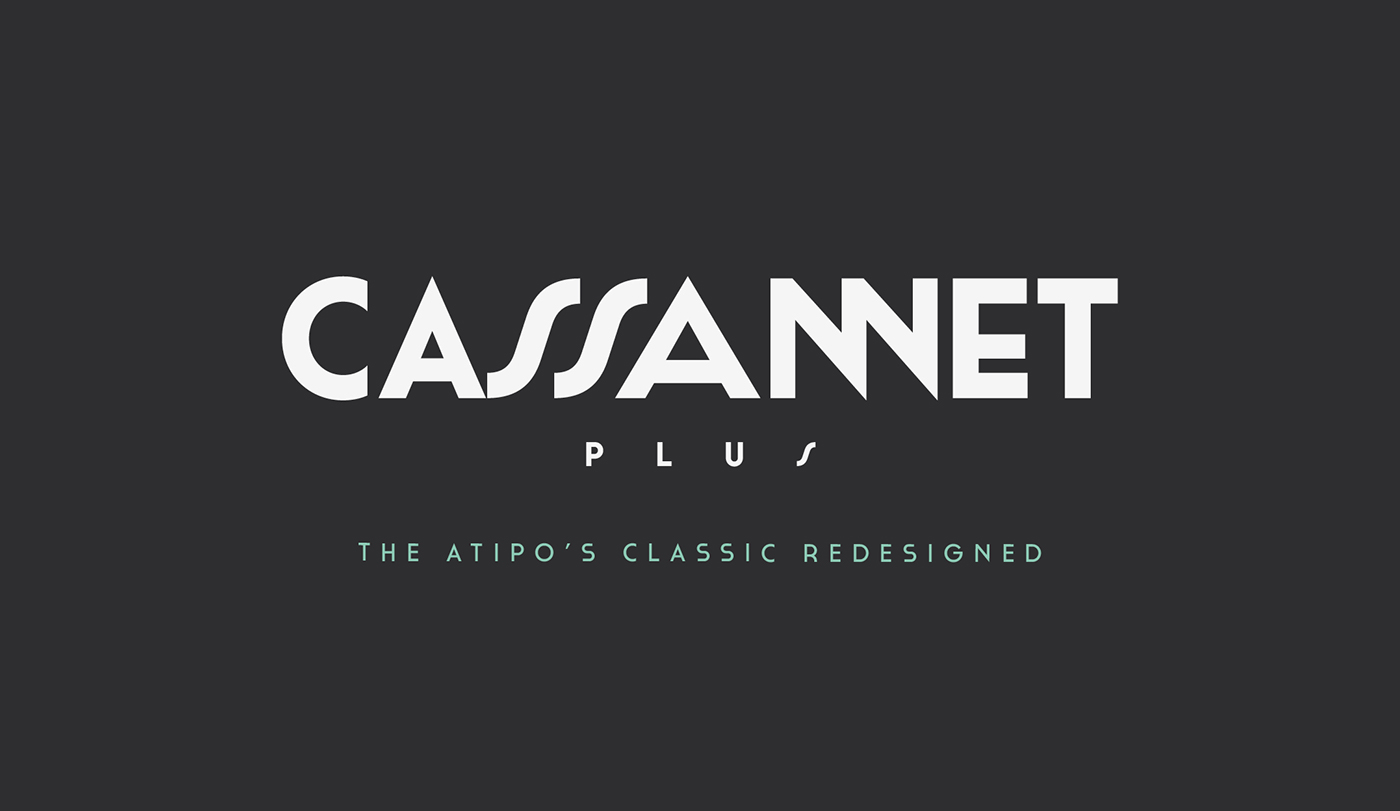
Выбираем шрифт для логотипа
Как выбрать шрифт и сделать логотип самому?
Одним из ключевых компонентов хорошего (и даже плохого) логотипа является Его Величество Шрифт. Именно он передает «message» дизайнера, правильно воспринявшего чаяния заказчика, потенциальной потребительской аудитории.
Выбирать шрифт необходимо, придерживаясь если не правил, то, как минимум, принципов. Но для того, чтобы не «увязнуть» в профессиональной терминологии, необходимо познать ее хотя бы отчасти. Только так Вам откроется ответ на вопрос – как сделать логотип самому?
Какими же бывают эти «заветные буковки»?
Есть шрифты, которые имеют так называемые «засечки»
В плеяде профессиональных дизайнеров «бытует поверье», что «засеченный» шрифт помогает держать внимание на строке. Ключевой характеристикой такого шрифта является переход от более толстых линий к тонким.
Как, например, здесь:
Без засечек — Sans Serif
Словно в противовес им созданы шрифты, не имеющие засечек, что, тем не менее, придает им свою привлекательность.
Взгляните на эту эстетику прямых углов, четких, ровных линий. Она имеет право на существование!
Где сгодится такой шрифт? Везде! Большинство мировых брендов используют в логотипе шрифт без засечек. Он не заменим там, где требуется подчеркнуть и поставить во главу угла элемент делового стиля.
Рукописные шрифты
А что же рукописные шрифты? Здесь всё сложно. С одной стороны они могут педалировать особую «человечность» бренда, с другой – именно рукописный шрифт, порой, заявляет изящество, роскошь. Вот вам пример – Cadillac.
Разве не похоже это на стильную роспись миллионера, которому совершенно не важно, будет ли прочитана его фамилия или нет?
Архаичный шрифт
Приходилось ли Вам замечать, что мы живем в удивительное время – когда во времени настоящем, сегодняшнего – самый минимум. Нам показывают сериалы о советских временах. В тренде герои вчерашних лет. Заглянем в ГУМ! Нас накормят советским мороженым. Мы можем выпить чаю в советских буфетах, с отнюдь не советскими, разумеется, ценами.
Архаичный шрифт сбитой машинки в логотипе? Почему бы нет, если Вы хотите подчеркнуть, что работаете в отрасли со времен царя Гороха? Смотрится вполне читабельно.
Декоративный шрифт
И, наконец, декоративный шрифт, с его поистине неисчерпаемыми возможностями.
Вариаций декоративных шрифтов миллионы. И оттенков производимого на потенциального потребителя впечатления ничуть не меньше. С помощью логотипа с таким шрифтом, при правильном подходе, можно легко выделиться среди конкурентов. Что Вы хотели бы видеть в логотипе? «Веселуху» или романтичность? Торжественность или щепотку пафоса? Историческую составляющую или агрессивный hi-tech?
Практически каждый день появляется новый интересный шрифт. Но радует пользователей он недолго, так как надоедает всем еще быстрее, чем популярная мелодия, установленная на телефон.
Так как же выбрать нужный шрифт?
Какой бы знак не был выбран, к нему уже подобран оптимальный шрифт. Но всё же существуют несколько общих правил, о которых стоит рассказать:
- Шрифт обязательно должен отвечать направлению бизнеса. Представьте себе банк с веселенькими «диснеевскими шрифтами». Возникнет ли доверие у потенциального клиента? Нет. Он испугается, что его могут «весело прокатить» на «финансовой карусели». А теперь вообразите надпись «Детские аттракционы», которая имеет лого а-ля Linked In? Проще всего выбрать «вкусный» шрифт для бизнеса, сходив к конкурентам или открыв их сайты, чтобы посмотреть, какие шрифты являются популярными в избранной Вами сфере бизнеса.
- Читабельность шрифта должна быть по умолчанию безупречной. Уменьшите Ваш логотип до минимума. Хорошо ли при этом читается шрифт? Если да, Вы сделали правильный выбор.
- Напишите несколько строк обычного текста. Проверьте четкость шрифта «на глаз». Не сливаются ли буквы? Что происходит при сжатии? Он смотрится и читается хорошо? Мы Вас поздравляем.
- Как согласуется шрифт с другими элементами логотипа? Часто можно наблюдать распространенную картинку: изящная иконка и массивный, никак не согласующийся с нею шрифт. Такой логотип может вызвать лишь ироничное отношение.
- Вы нашли не один, а несколько хороших шрифтов? Мы рады за Вас. Но не стоит использовать в логотипе больше одного. В крайнем случае будут уместны два шрифта. Но, все же, по нынешним меркам это много.
- Насколько типичен Ваш шрифт? Представляет ли он собой клише? Если Вы используете Comic Sans для того, чтобы сделать надпись на логотипе, который будет принадлежать компании, занимающейся развлечениями и юмором, это не очень правильно.
- Не стоит превращать подбор шрифта для логотипа в фанатичную «погоню за трендом». Не обязательно использовать шрифт, появившийся вчера или находящийся на пике популярности. Всё новое рано или поздно становится старым.
14. Монтсеррат
Монтсеррат — воплощение городской типографики начала 20 века. Дизайнер Джульета Улановски создала этот шрифт, чтобы сохранить свой город Монтсеррат на века.
Таким образом, в местах, где тонкие шрифты плохо масштабируются (например, фавикон), у вас есть возможность использовать свою монограмму или символ!